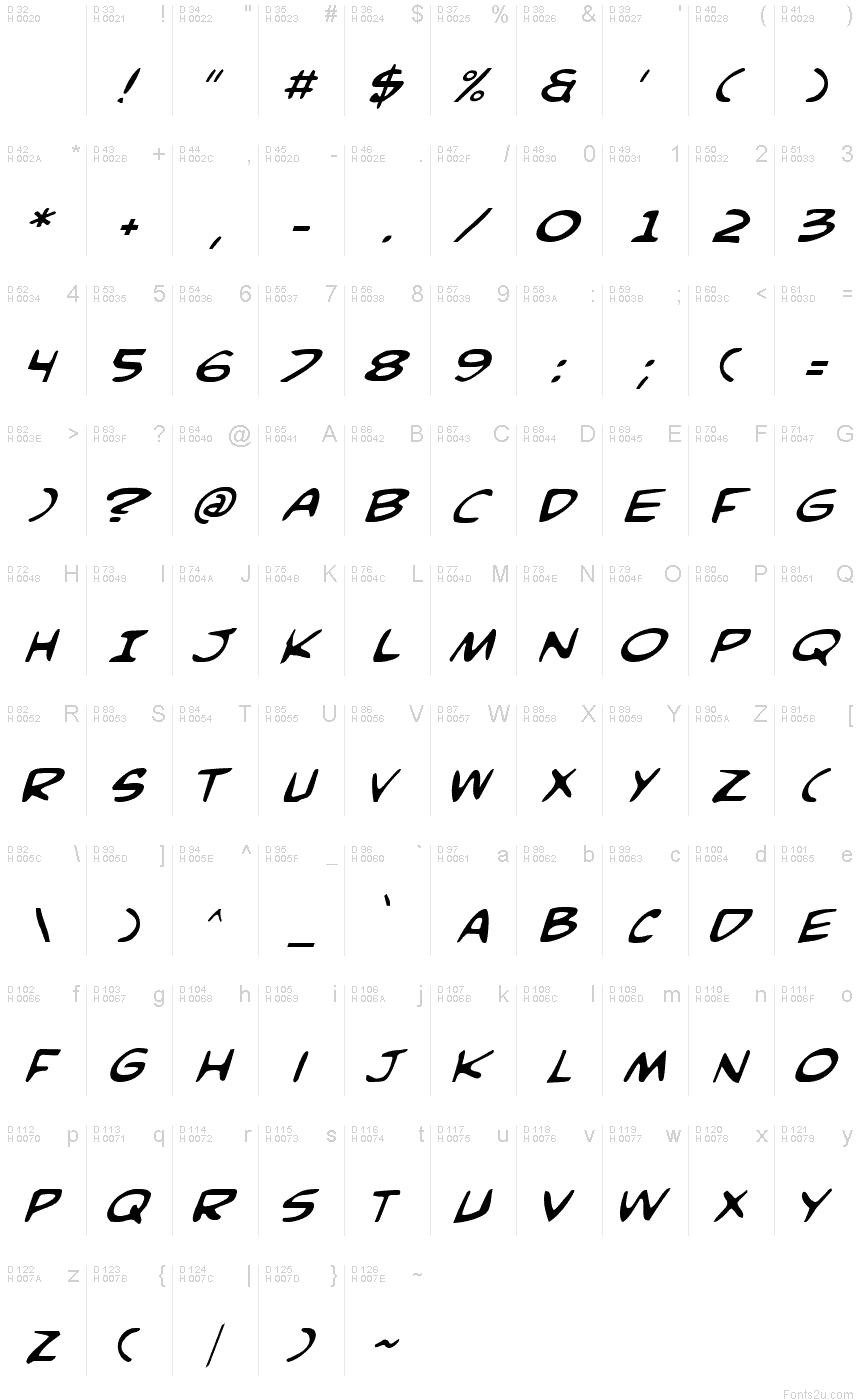
Comic Book Commando Italic
Font Comic Book Commando Italic od Iconian Fonts to darmowy krój pisma w stylu komiksowym, który oddaje szybkość i dynamikę sceny akcji. Jego ciężkie, pochylone do przodu znaki wyglądają, jakby zostały nakreślone jednym szybkim ruchem, a zaokrąglone, przesycone atramentem kształty nadają mu zabawny, a nie surowy charakter. Całość ma w sobie wyrazisty, kinetyczny rytm, który natychmiast przywodzi na myśl akcję, humor i energię klasycznych komiksów.
Comic Book Commando Italic świetnie sprawdza się na okładkach komiksów, w logotypach superbohaterów, na plakatach arcade, w miniaturach na YouTube, projektach naklejek, gadżetach dla dzieci czy efektownych ulotkach. Ten darmowy font najlepiej prezentuje się w większych rozmiarach, gdzie skośny ruch może w pełni wybrzmieć; spróbuj zestawić go z prostym krojem bezszeryfowym, aby nagłówek był wyrazisty i czytelny.